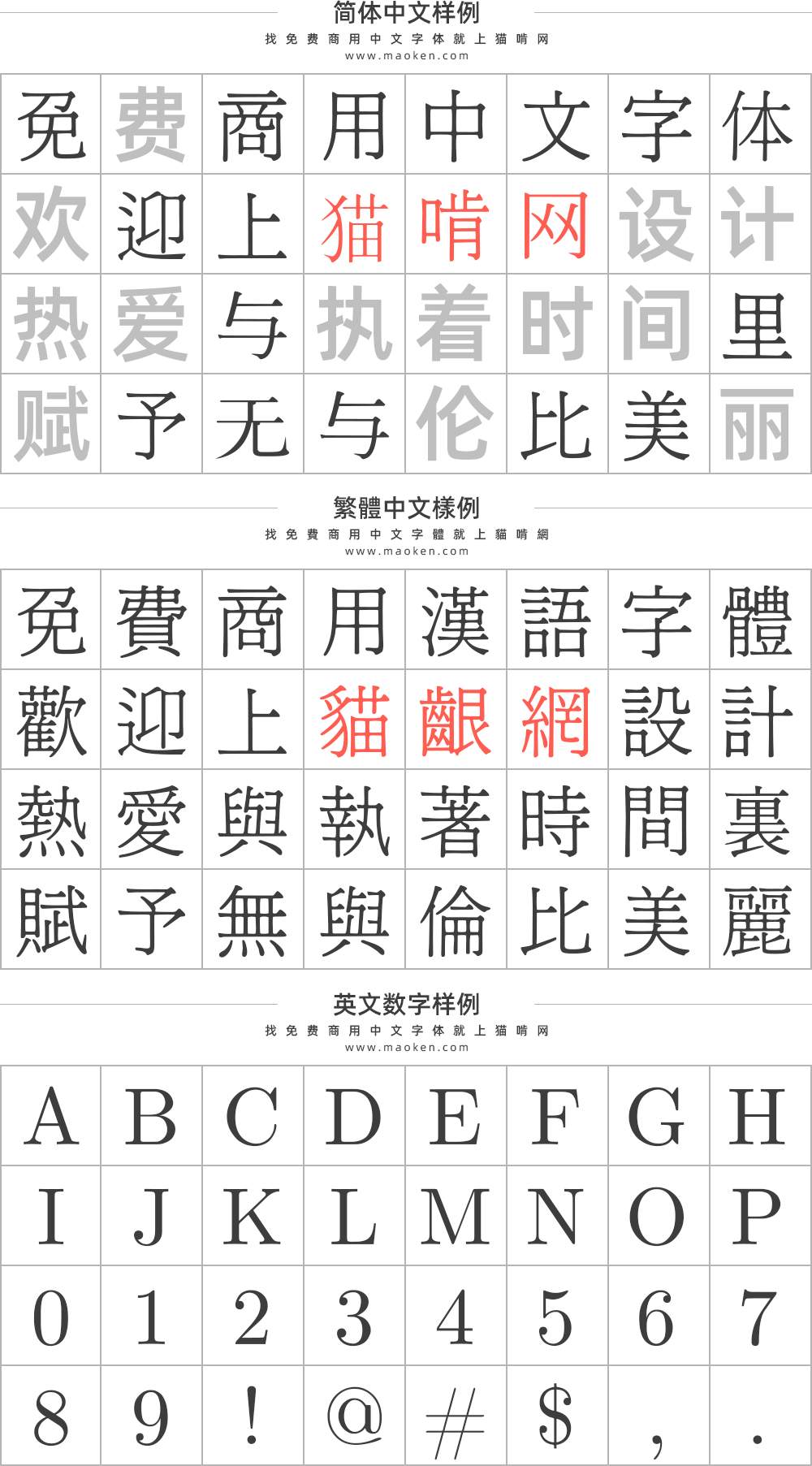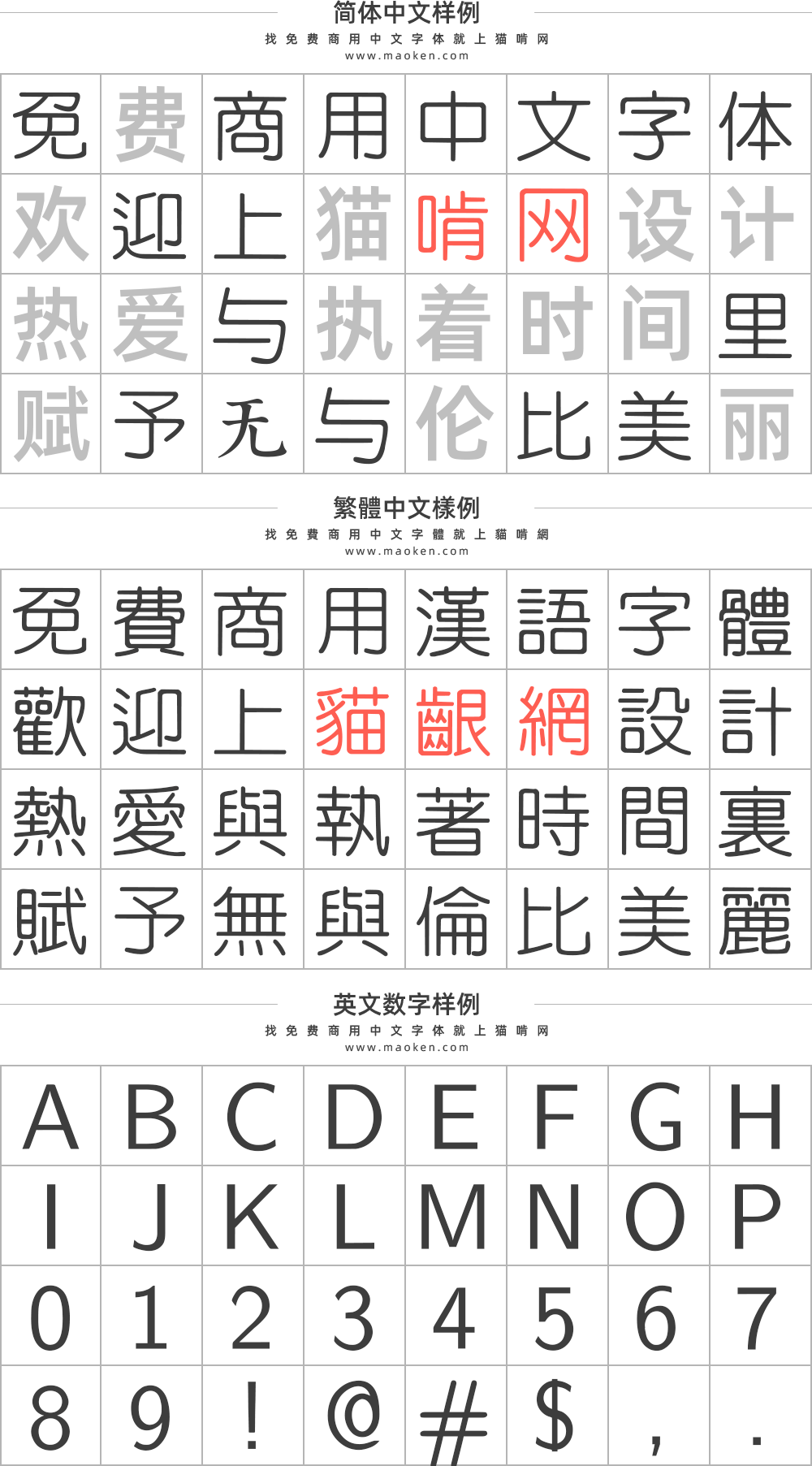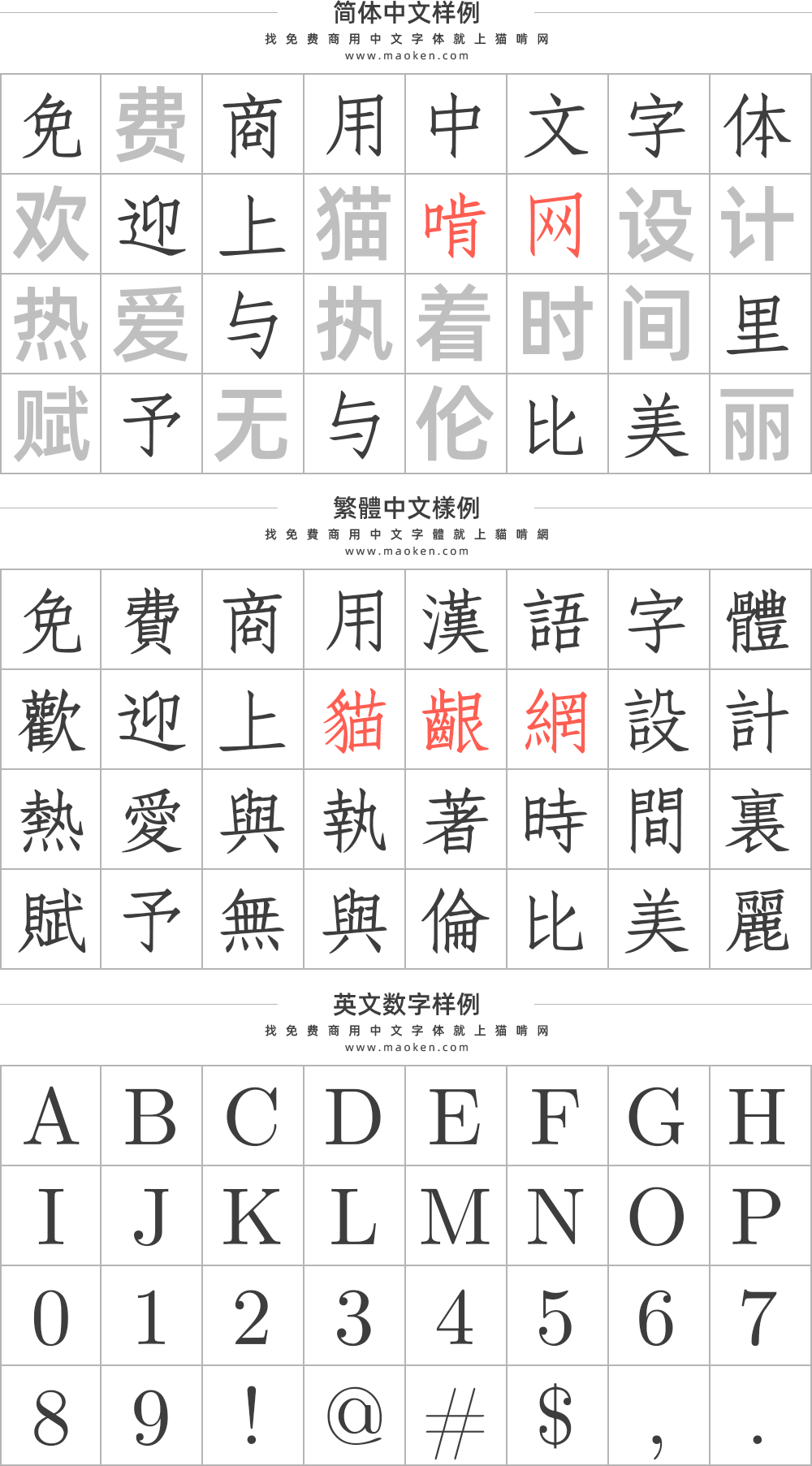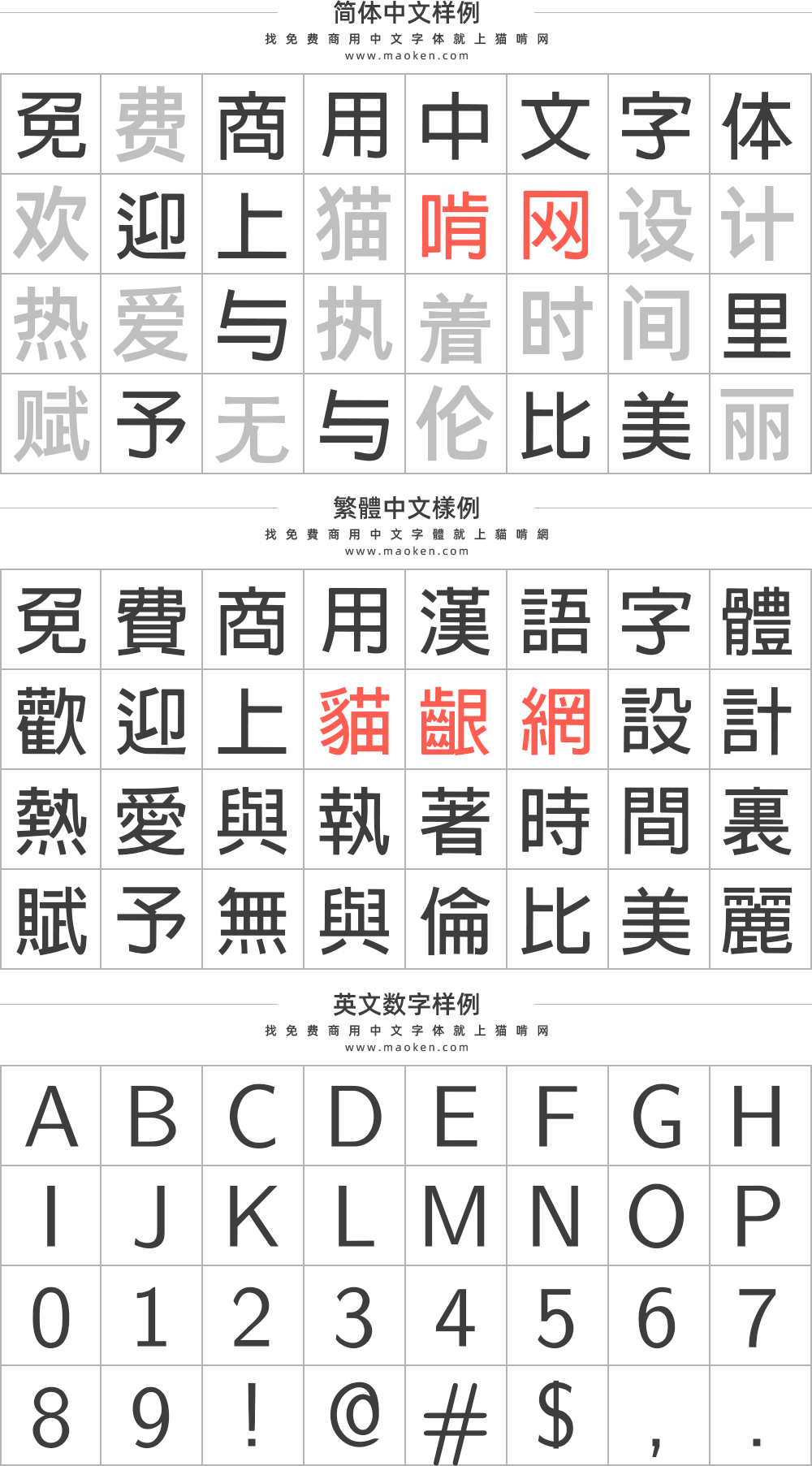
《台湾cwTeX字体系列》字体来源可能是盗版字体 不建议商业使用
cwTeX-Q-Fonts字体是一款电脑字体包,该字体库有着非常仿古的特色,并且非常适合印刷用途,只是对于简体字兼容不佳,本字体开源免费商用,有需要的用户可以下载使用!
cwTeX 字型最初是由Tsong-Min Wu及Tsong-Huey Wu于1999至2004年间制作并以GNU GENERAL PUBLIC LICENSE Version 2 or latter发布。在2005至2007年间,Edward G.J. Lee对该字型进行过整理。而本套字体cwtex-q-fonts自2008年起由Chen-Pan Liao开始维护。
这款字体比思源黑体还要早出现,包括 cwTeX Q FangSong(仿宋体)、cwTe Q XHei(黑体)、cwTeX Q Ming(明体)、cwTeX Q Yuan(圆体)和cwTeX Q Kai(楷体)五种。
cwTeX 中明体
cwTeX 中楷体
cwTeX 中圓体
cwTeX 中仿宋体
cwTeX 粗黑体